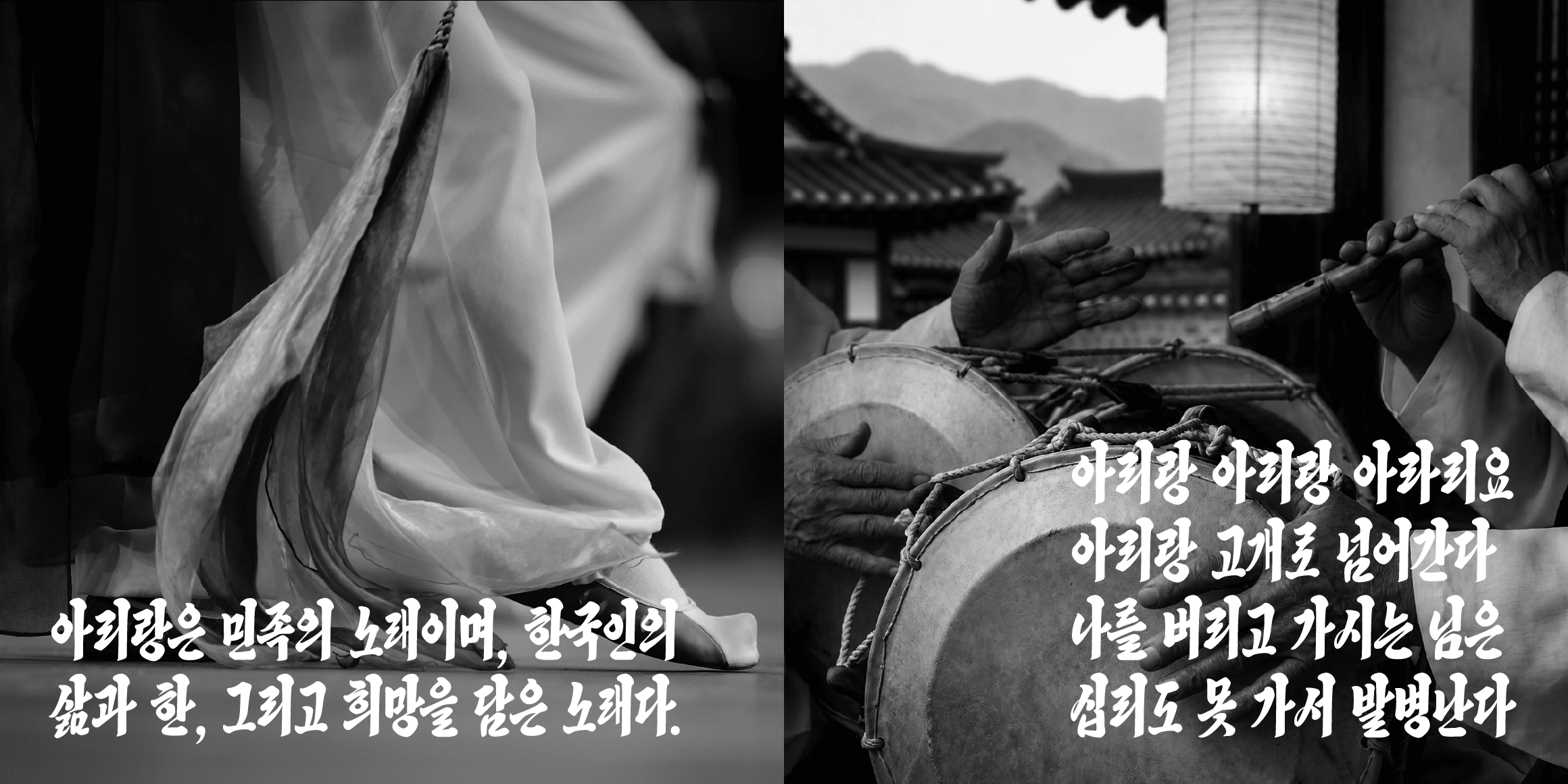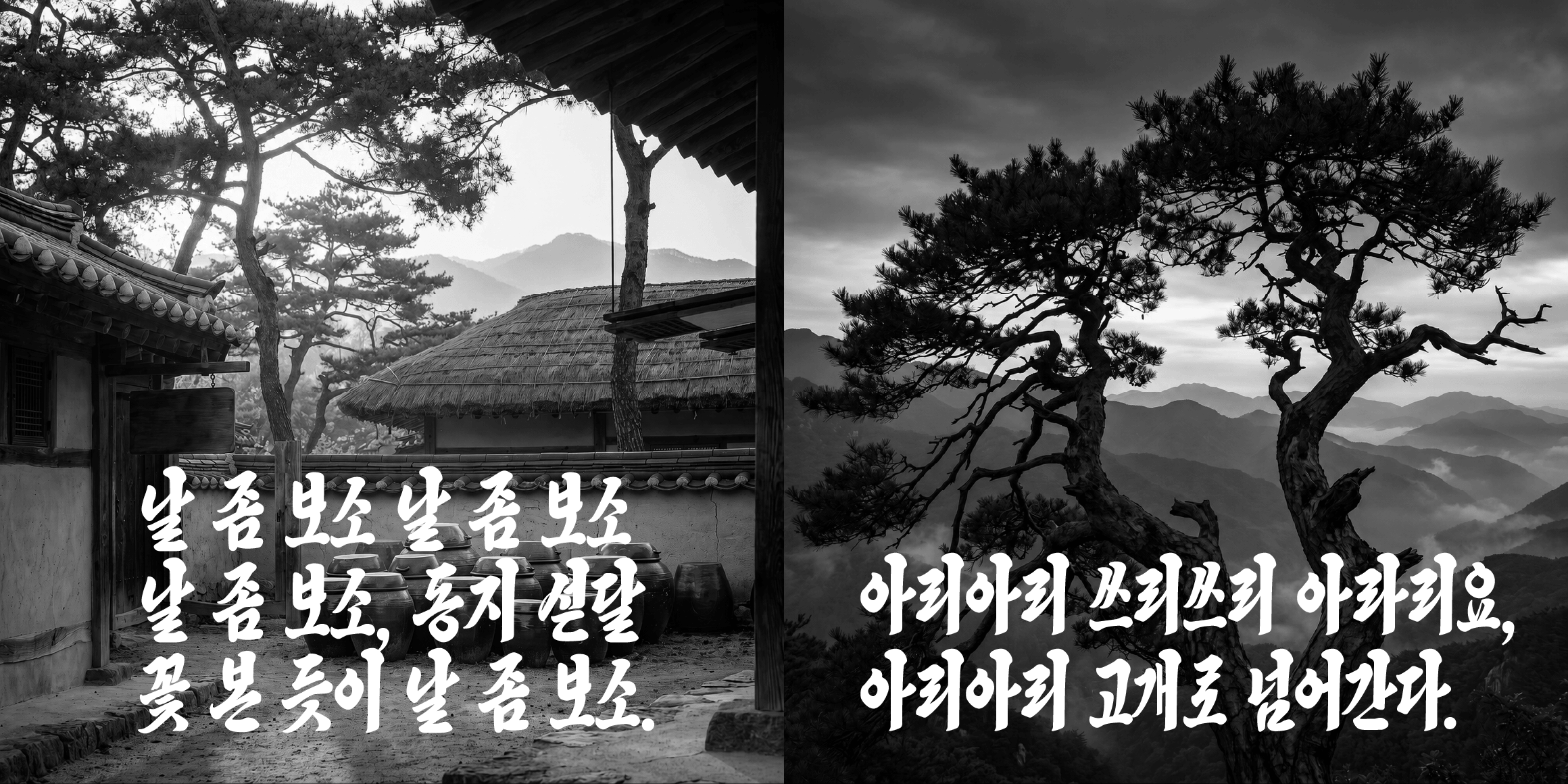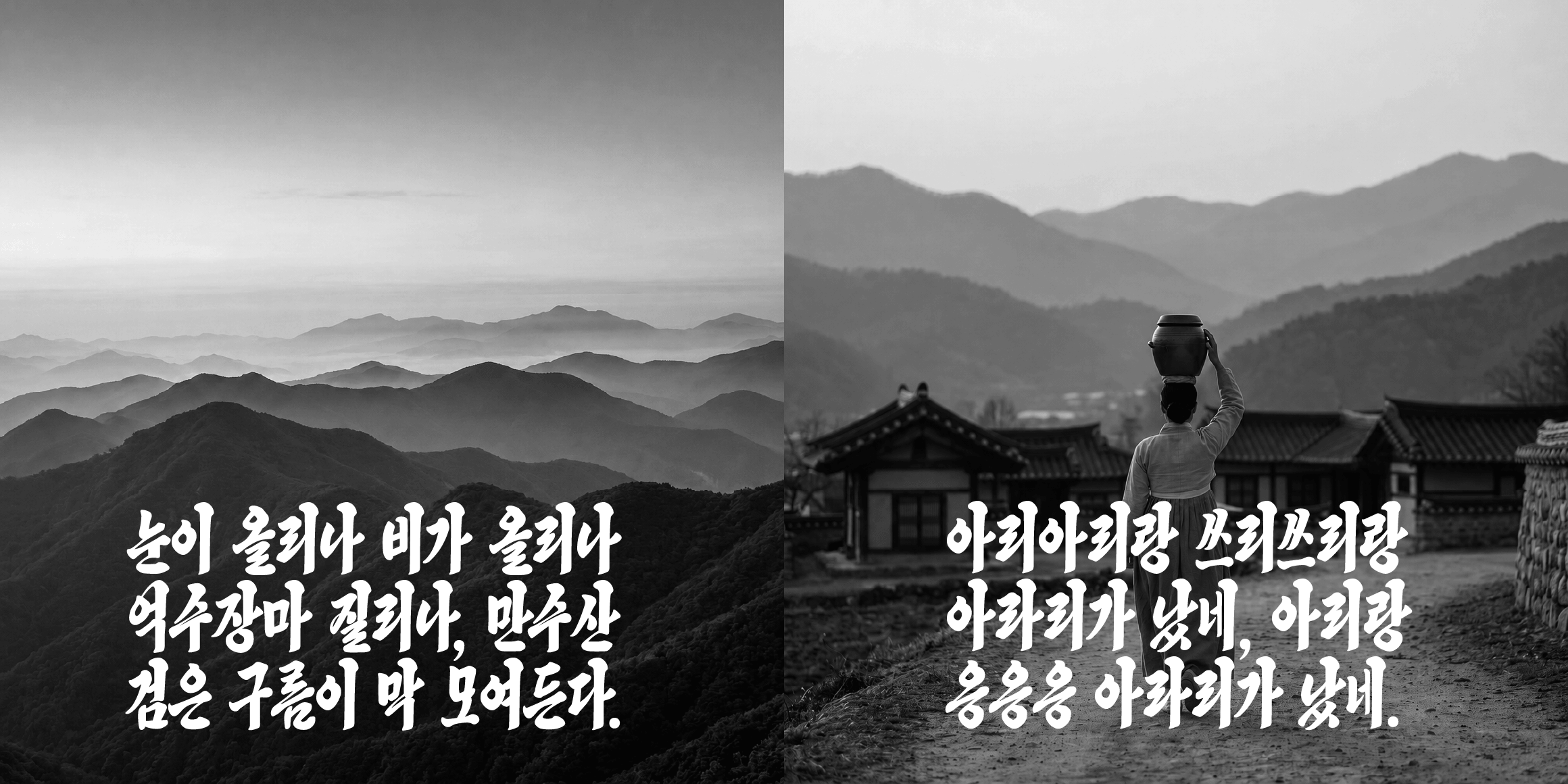
아리랑
Joonfont
분류 Serif,부리
출판영상고전적
힘 있는 붓터치와 유연한 흘림이 돋보이는 서체입니다. 역동적인 기울기 변화와 필압의 차이로 강인한 분위기를 연출하며, 전통미와 현대적 가독성의 조화로 따뜻한 손맛을 전해줍니다. 한글 커닝 적용으로 조밀함이 강조됩니다.
• Serif,부리
• 아리랑 / Arirang